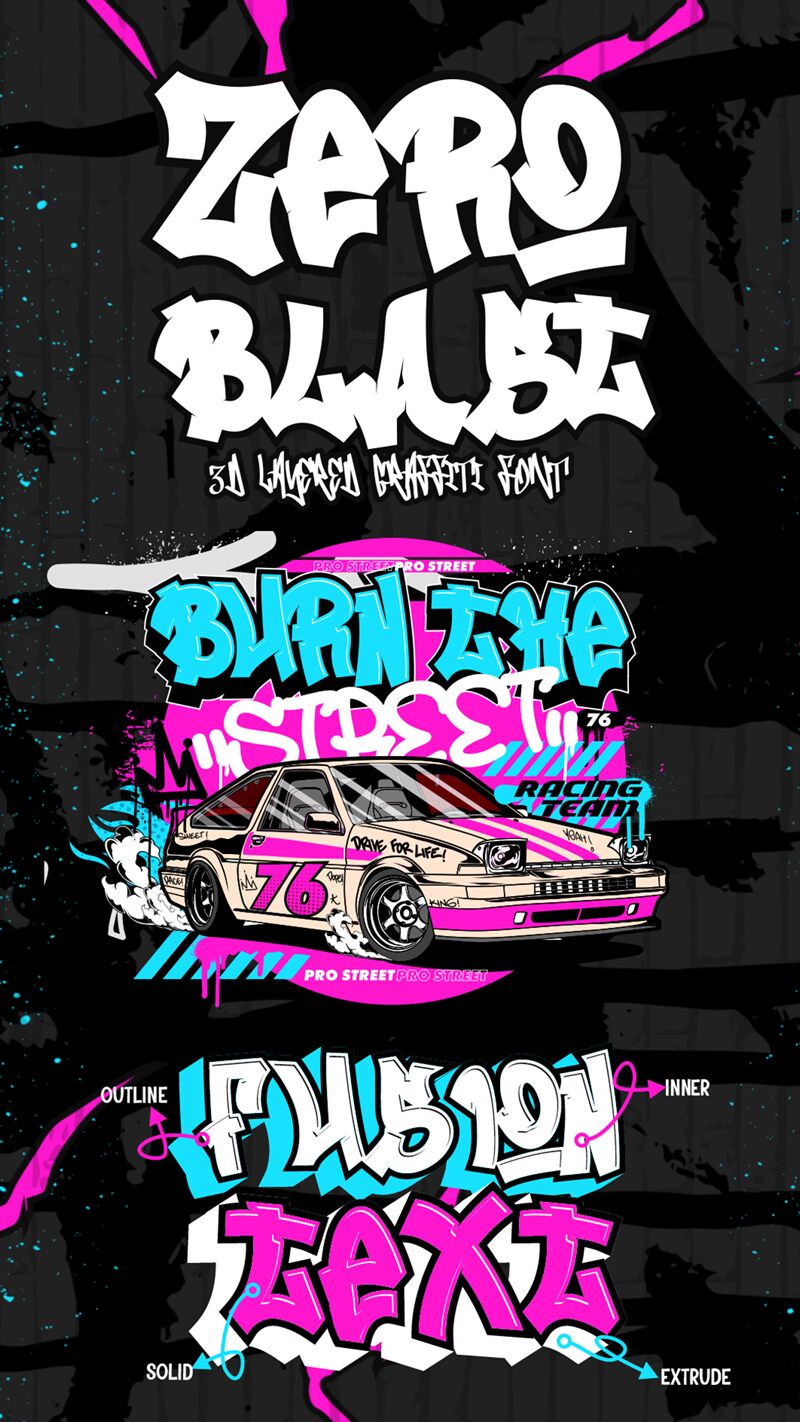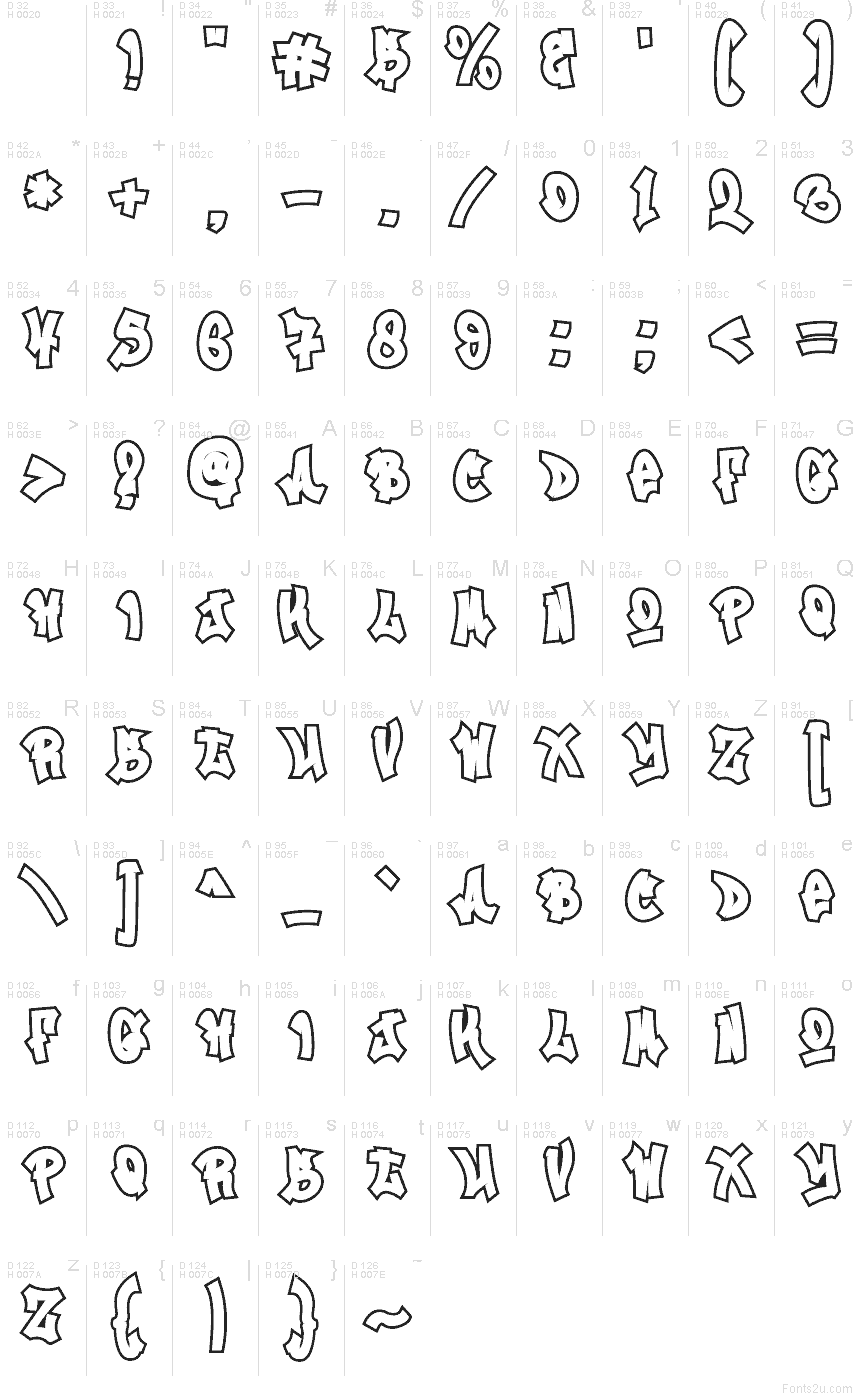
Zero Blast Outline di Muhammad Panji Ramdhani (Figuree Studio) è un font graffiti gratuito con l'attitudine incisiva di uno sticker-tag. Le sue forme corpose e il contorno audace conferiscono a ogni parola un look ritagliato e nitido, come se il tratto di un pennarello fosse stato sollevato e schiaffato direttamente su un muro. Il ritmo leggermente irregolare mantiene il font vivo e umano, mai sterile.
Zero Blast Outline brilla su loghi streetwear, miniature YouTube, poster di eventi, grafiche per skate, copertine di album, intestazioni per team esports e pubblicità social d'impatto. Abbina questo font gratuito a una sans condensata e pulita per i testi di supporto e ingrandiscilo in modo che il contorno rimanga bold e leggibile anche su sfondi complessi.